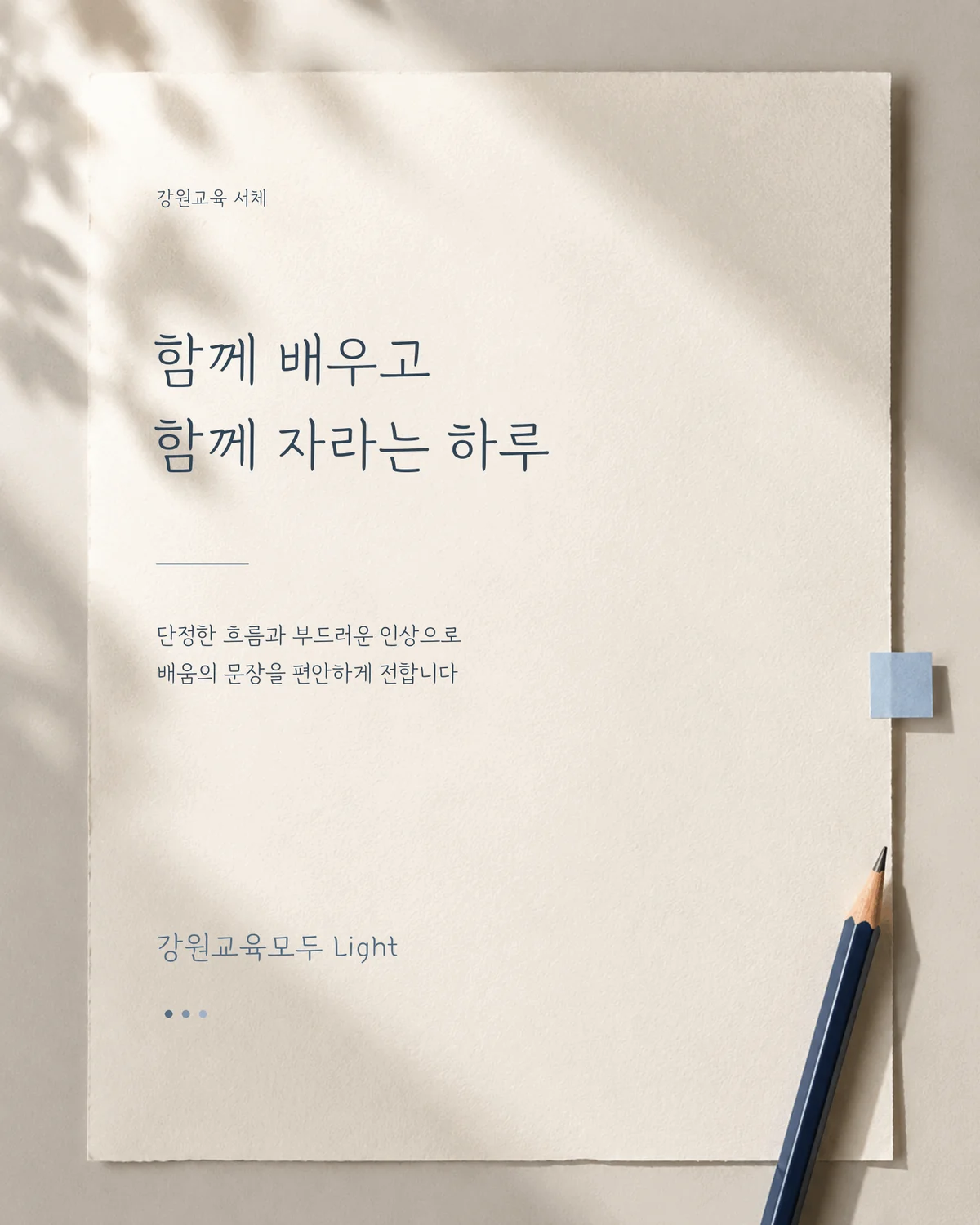
강원교육모두 — 강원특별자치도교육청에서 배포하는 무료 폰트입니다. 부드러운 명조 구조에 단정한 글자 짜임을 더해 편안한 인상을 주는 서체
강원특별자치도교육청이 2020년 4월에 배포한 서체로, 헤움디자인이 만들었습니다. 만든 계기가 이 서체의 성격을 그대로 말해 줍니다. **코로나19로 온라인 개학이 확대되면서 교사들이 수업 자료를 만들 때 글꼴 저작권 문제를 겪자, 교육청이 일정을 앞당겨 배포**한 것입니다.
이름의 모두를 두고는 오해가 있습니다. 접근성을 뜻하는 말이 아니라 교육청 슬로건인 모두가 빛나는 강원교육에서 왔습니다.
교육청이 쓴 조형 설명은 없고 용도만 밝혀져 있습니다. Bold는 표지 제목이나 홍보물 제작에 활용하고, Light는 볼드와 동일한 형태이나 가늘게 제작되어 문서 본문 작성에 적합하다는 것입니다. 이름만 보고 고딕으로 짐작하기 쉬운데 파일에서 재어 보면 **부리가 있는 바탕 계열**이고, 낱자가 폭보다 높이가 커서 세로로 서 있으며 획이 가늘어 자면을 채우는 비율이 낮습니다.
굵기는 두 가지이고 현대 한글 11,172자를 모두 담았습니다. 같은 가족으로 강원교육튼튼체와 함께, 교사와 학생의 손글씨 공모전 당선작을 옮긴 현옥샘체·새음체가 있습니다. 무료로 쓸 수 있고 폰트 파일 판매만 금지됩니다.